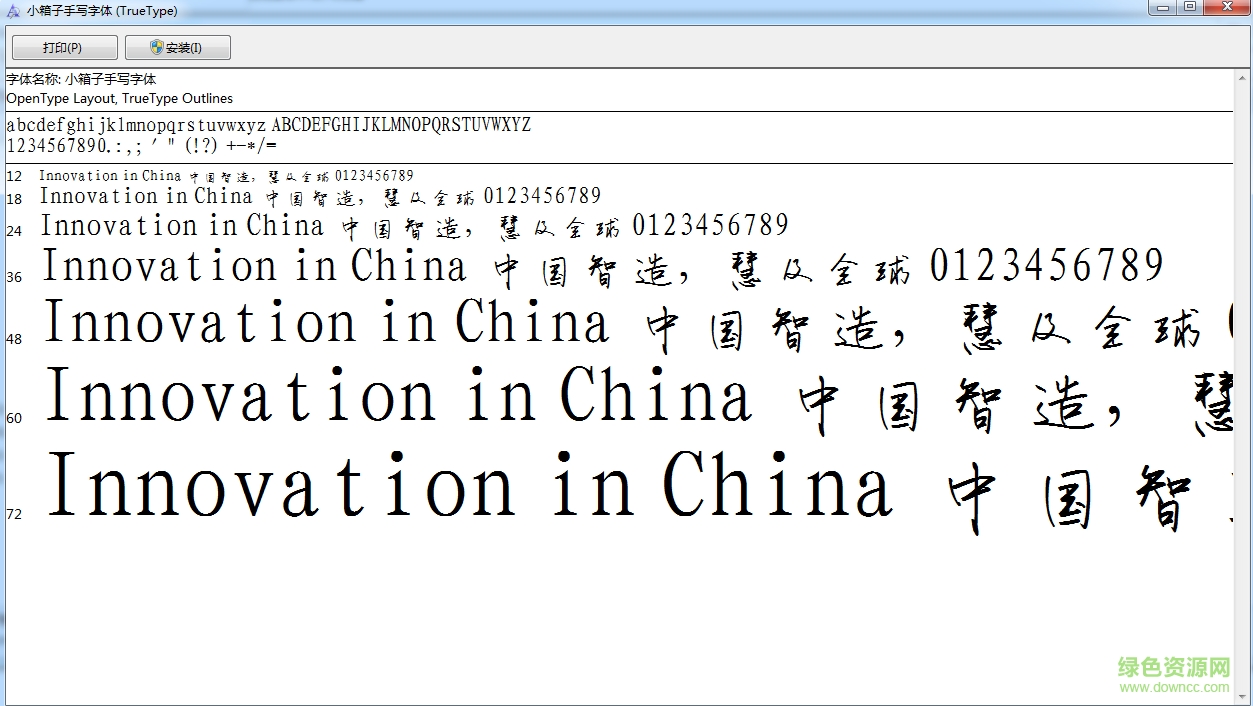
小箱子手寫字體是一款TTF格式的手寫字體,是作者林哲祥自創(chuàng)的行草字體,簡潔清爽的書法讓你閱讀觀賞更加愉悅,喜歡的朋友快來綠色資源網(wǎng)下載吧!
手寫字體一直都是信筏書簽,設(shè)計(jì)美工的左膀右臂。但在這個(gè)互聯(lián)網(wǎng)時(shí)代,手寫的字體雖然小眾,卻一直是以不可磨滅的重要意義存在。其一中國書法文化博大精深,歷史源遠(yuǎn)流長。其二就是與眾不同的個(gè)性化。所謂:陰影越是豐富,立體感越強(qiáng)。在普羅大眾眼里“與眾不同”就是一種個(gè)性化。
基于自身書法功底,以行楷手寫這套字體,在制作字體庫的時(shí)候,對(duì)字體大小和位置進(jìn)行微調(diào),這樣輸入時(shí)字體視覺上會(huì)錯(cuò)開 ,呈現(xiàn)出來的書寫效果更接近真實(shí)手寫。
近期將完成個(gè)人的第二套行草字體,達(dá)到常用詞組字體之間“筆斷意連”的行云流水效果。也借此平臺(tái)希望把個(gè)人對(duì)書法、手寫字體的理解傳遞給懂得欣賞的人、需要的人。